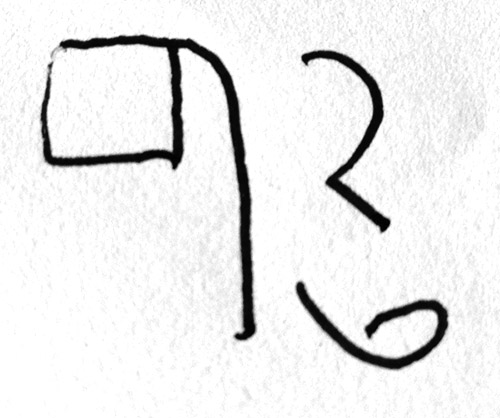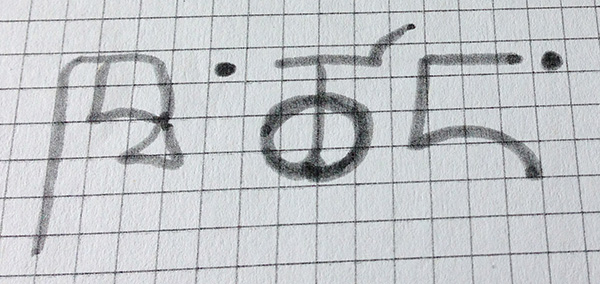
Zwei Wörter auf Tibetanisch?
Bei einer Kurzgeschichte die ich gerade layoute, kommen auf zwei Stellen tibetanische Schriftzeichen vor. Ich habe nur ein JPEG davon wie's aussehen soll. Ich hab versucht, mir tibetanische Schriften aus dem Netz herunter zu laden und die Zeichen dann zu suchen über die Glyphen. Stellt sich aber als schwieriger heraus als gedacht. Ist hier vielleicht einer der Erfahrung damit hat?
Ich hab JPEGs der zwei Wörter angehangen:
Das erste müsste eigentlich »Krähennest« heißen.
Das Zweite soll wohl »GAU« heißen.
Es kommt drauf an, mit welcher Schrift du das setzen möchtest.
Die schönste tibetische Schrift ist die von Tony Duff, in der ich dir das setzen kann.
Ich habe keinerlei Erfahrung mit der tibetischen Sprache. Mich hat aber interessiert, ob ich irgendwie mit den fremden Zeichen weiterkomme. Hinter dem ersten Bild steckt wohl dieser Begriff (tatsächlich "gau" ausgesprochen):
Beim zweiten Begriff ist die Sache unsicherer. Zu identifizieren ist "Krähe":
Auch "Nest" habe ich gefunden:
Und wenn "Vogelnest" diese Kombination hat ...
... dann ist in "Krähennest" vielleicht tatsächlich nur ein Zeichen auszutauschen.
Danke schon mal für die Antworten. Interessant :-) Also tibetanische Fonts habe ich  etliche gefunden aber wenn man keine Ahnung hat, sucht man einfach ziemlich planlos in den Glyphen rum. Ich hatte noch diese Website gefunden:
@ Gerd: Das wäre super wenn du mir das vektorisiert setzen könntest. Schrift ist egal. Wenn du sagst dass die von Tony Duff die Schönste ist, dann die :-)